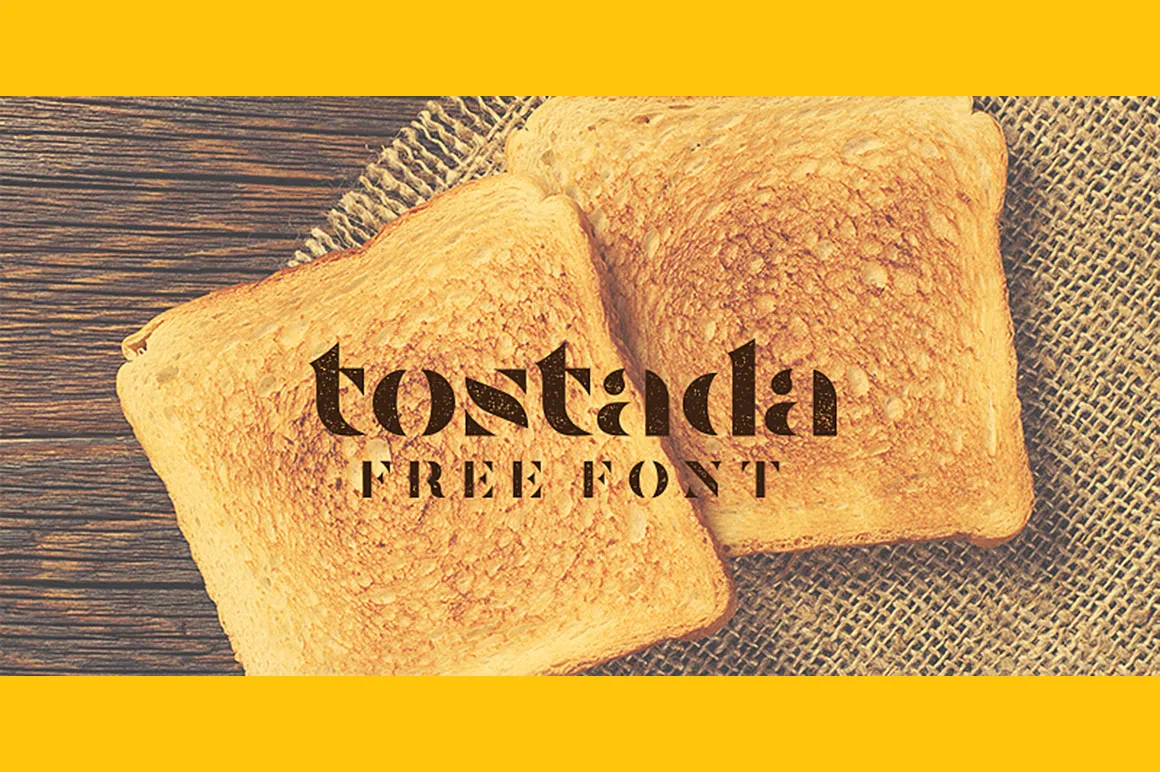
A Tostada Font é uma elegante fonte do tipo display criada pelo designer Hamilton. Esta fonte traz uma vibe vintage única, perfeita para projetos criativos inovadores. Com seu estilo vintage distintivo e personalizado, a Tostada Font é ideal para qualquer projeto onde um ar nostálgico e sofisticado seja desejado. Seja para marcar um livro de receitas antigo ou criar uma identidade visual moderna que remete aos anos 50, esta fonte traz o charme dos tempos vivos em seu design. Descubra a forma única da Tostada Font e inspire-se com seus tons vibrantes e sua personalização diferenciada. Instale-a hoje e experimente os benefícios de uma fonte do tipo display moderna e vintage.